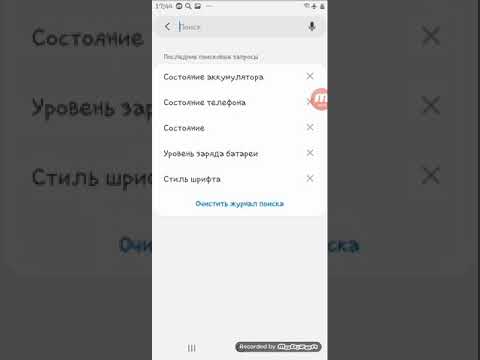
Как изменить шрифт на Android
Изменение шрифта — стандартная возможность для владельцев устройств с системой Android.
Системный шрифт имеет четыре основных параметра: размер, степень жирности, начертание(прямое или курсив) и стиль шрифта.
В зависимости от модели устройства и версии системы, настраиваемые параметры могут отличаться.
Размер шрифта можно изменить на любом устройстве, а для смены стиля, скорее всего, понадобится специальное приложение. По умолчанию система Android использует стиль Roboto.
Как изменить размер шрифта
Эта опция доступна для всех Android устройств. Чтобы изменить размер шрифта, откройте настройки. В разделе “Экран” выберите пункт “Размер шрифта”. Теперь вы можете отрегулировать размер текста. Обратите внимание, изменения коснутся всех текстовых элементов: от названий программ в меню до текста системных сообщений.
Как изменить стиль шрифта
На современных смартфонах и планшетах у пользователя обычно есть минимум несколько предустановленных шрифтов на выбор.
Кроме того, часто производители включают возможность добавлять сторонние шрифты, скачанные из интернета.
В зависимости от модели устройства, порядок изменения стиля шрифта может отличаться.
Устройства Samsung
Чтобы переключиться с одного стиля на другой, перейдите в настройки и найдите раздел “Дисплей”. Выберите опцию “Размер и стиль шрифта”. Обычно параметр “Стиль шрифта” имеет значение “по умолчанию”. Нажмите на параметр, чтобы изменить его.
В выпавшем списке отображаются доступные предустановленные стили. Здесь же можно загрузить дополнительные шрифты. Когда вы нажмете на “Загрузить шрифты”, откроется магазин с доступными вариантами для разных языков.
Устройства Huawei
На устройствах Huawei предустановлено системное приложение “Темы”, с помощью которого можно кастомизировать элементы системы.
Чтобы изменить шрифт, нажмите на иконку приложения “Темы” и удерживайте, пока не появится список опций. В нём выберите пункт “Стиль текста”. Откроется каталог с доступными шрифтами.
Устройства Xiaomi
Откройте настройки устройства и найдите раздел “Дополнительно”. В этом разделе выберите пункт “Шрифт”. Откроется каталог с доступными системными шрифтами.
Использование root-прав
По умолчанию система Android использует шрифт Roboto. Его настройки хранятся в папке /system/fonts в файле Roboto-Regular.ttf.
Самый простой способ изменить системный шрифт, имея root-доступ, — заменить файл со шрифтом Roboto на файл с нужным вам шрифтом (например, Yandex Sans).
Например, вы хотите заменить Roboto на Verdana. Для этого нужно скачать шрифт Verdana в формате TTF и переименовать файл в “Roboto-Regular.ttf”. Этот файл скопируйте в папку /system/fonts, заменив им оригинальный файл со шрифтом Roboto.
Перезагрузите устройство, после чего новый шрифт автоматически будет применён ко всем текстовым элементам системы.
Как изменить шрифт на Android
Как можно быстро «преобразить» свой смартфон без покупки нового? Можно установить новые обои для домашнего экрана или просто заменить мелодию звонка. Но есть и 3-ий способ – заменить стандартный приевшийся шрифт в мобильной операционной системе.
В большинстве случаев в Android по умолчанию установлен шрифт Roboto. Он был разработан Google и представлен широкой публике в 2012 году.
Чаще всего он всех устраивает, его любят за аккуратные ровные линии и четкость. Но всегда найдутся те, кто хочет выделиться из толпы.
Если вы причисляете себя к таким людям – эта статья для вас. Огромным преимуществом Android как ОС является полная «кастомизируемость». Система позволяет пользователю менять встроенные шрифты. Однако возможность замены шрифтов не всегда простая задача. Часто для этого необходимы дополнительные знания. В статье вы узнаете о двух способах установки шрифтов на Android: с помощью root-доступа и без него.
Шрифт и стиль шрифта являются взаимозаменяемыми терминами, используемыми разными производителями. Оба они обычно относятся к одному и тому же: способу отображения текста на вашем устройстве. Размер шрифта, с другой стороны, относится к тому, насколько большими или маленькими будут буквы на вашем устройстве.
Чтобы изменить цвет шрифта на устройстве Android, вам нужно изменить тему.